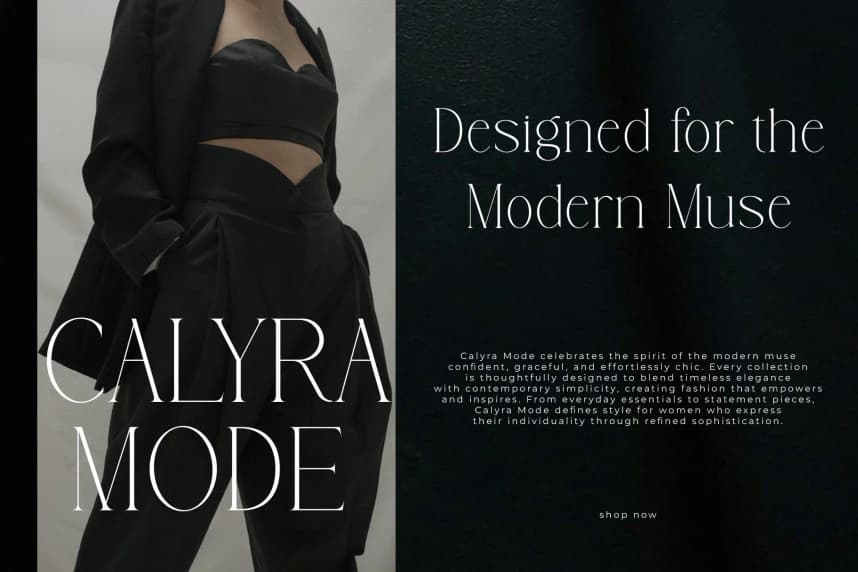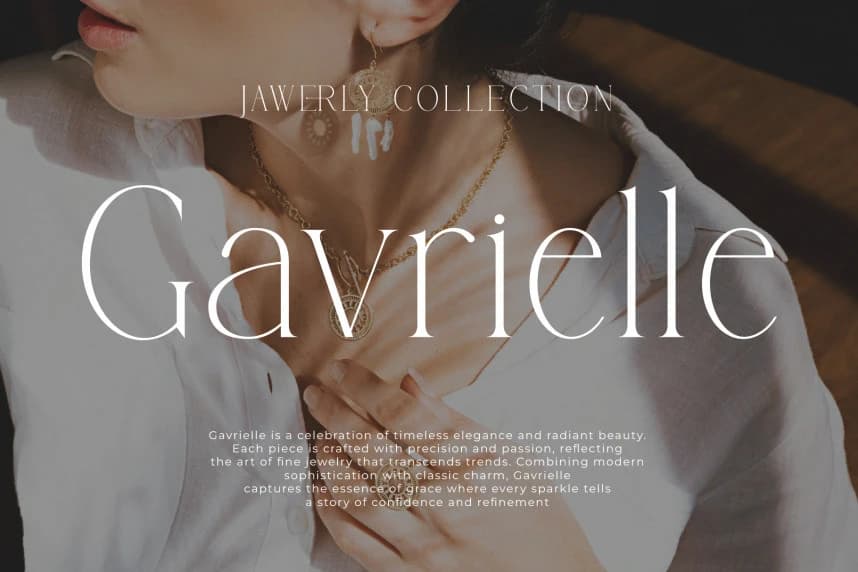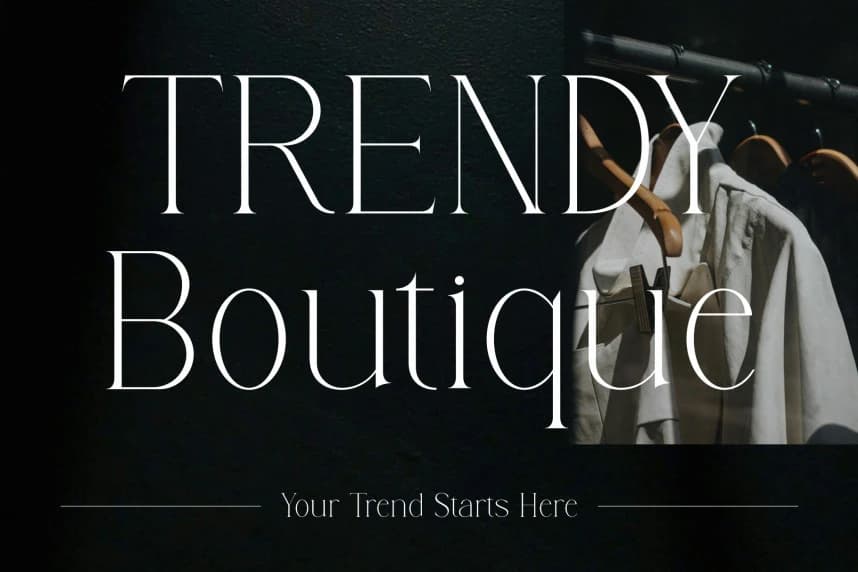
Framlir Font, sinematik bir display serif yazı tipi olup “lüks ve efsanevi” bir ruhu yakalar. Bu yazı tipi, jilet gibi ince hatlara sahip, yüksek kontrastlı harf formlarıyla karakterizedir; ritmik, akıcı eğriler ve klasik editoryal stil ile çağdaş stil arasındaki farkı köprüleyen benzersiz ligatürle
Framlir Font, sinematik bir display serif olarak “lüks ve efsanevi” bir ruhu yakalayan bir yazı tipidir. Bu yazı tipi, jilet ince saç çizgileriyle karakterize edilen yüksek kontrastlı uzun harf biçimlerine, ritmik akıcı eğrilere ve klasik editoryal stil ile arasındaki boşluğu köprüleyen benzersiz ligatürlere sahiptir.